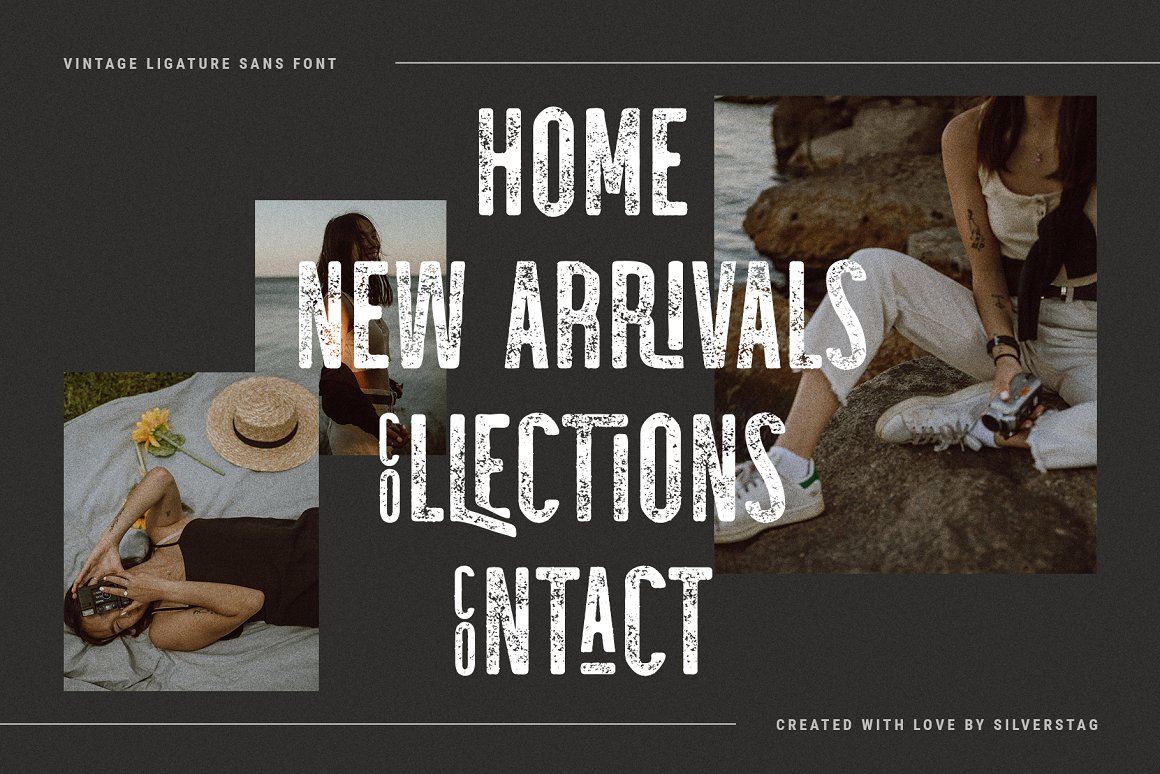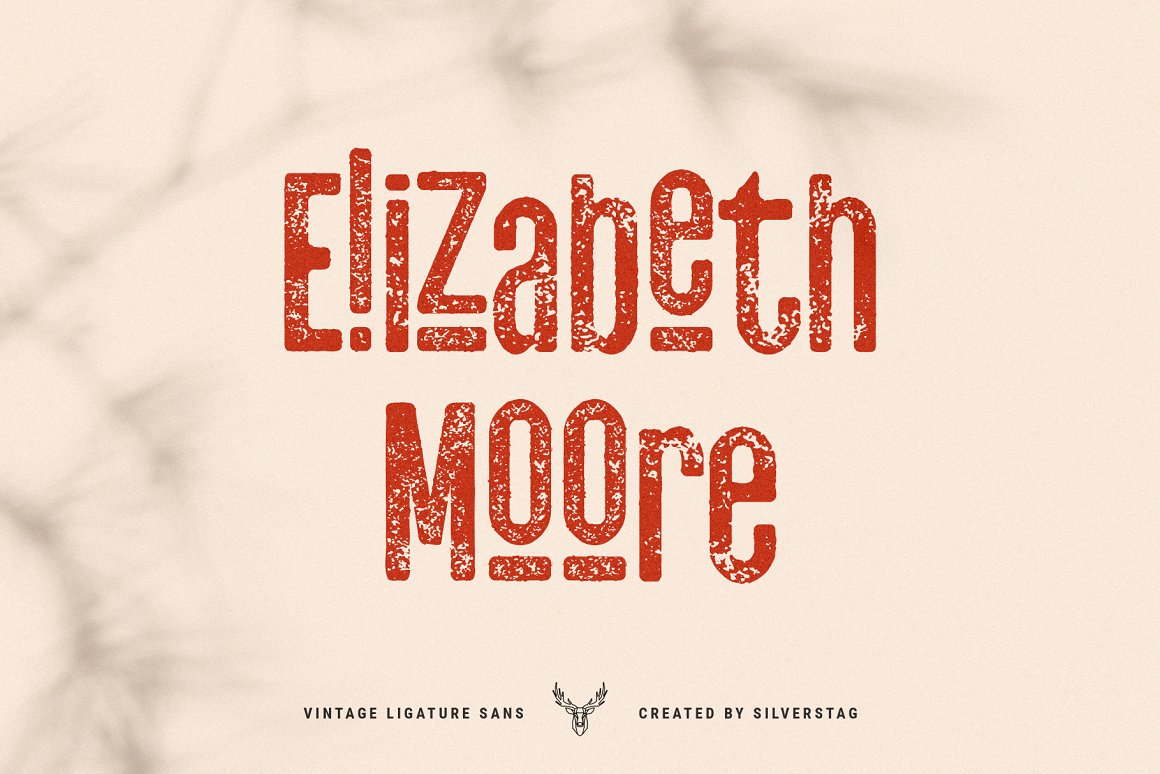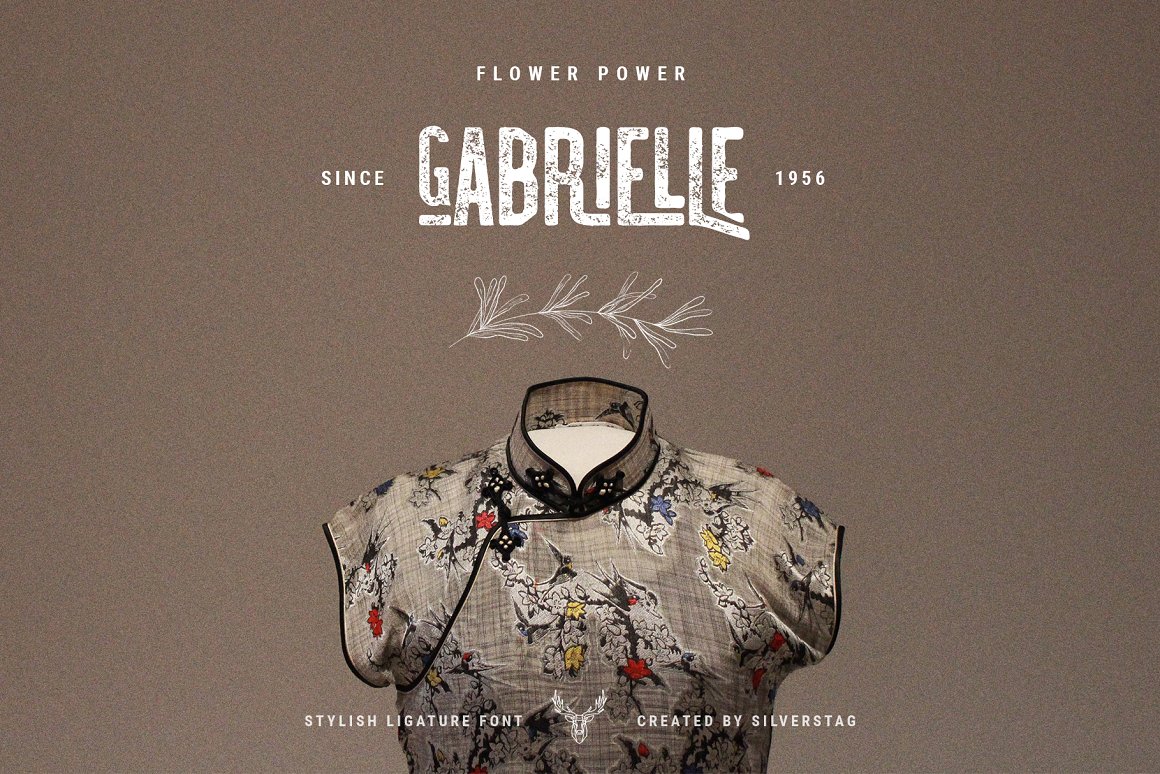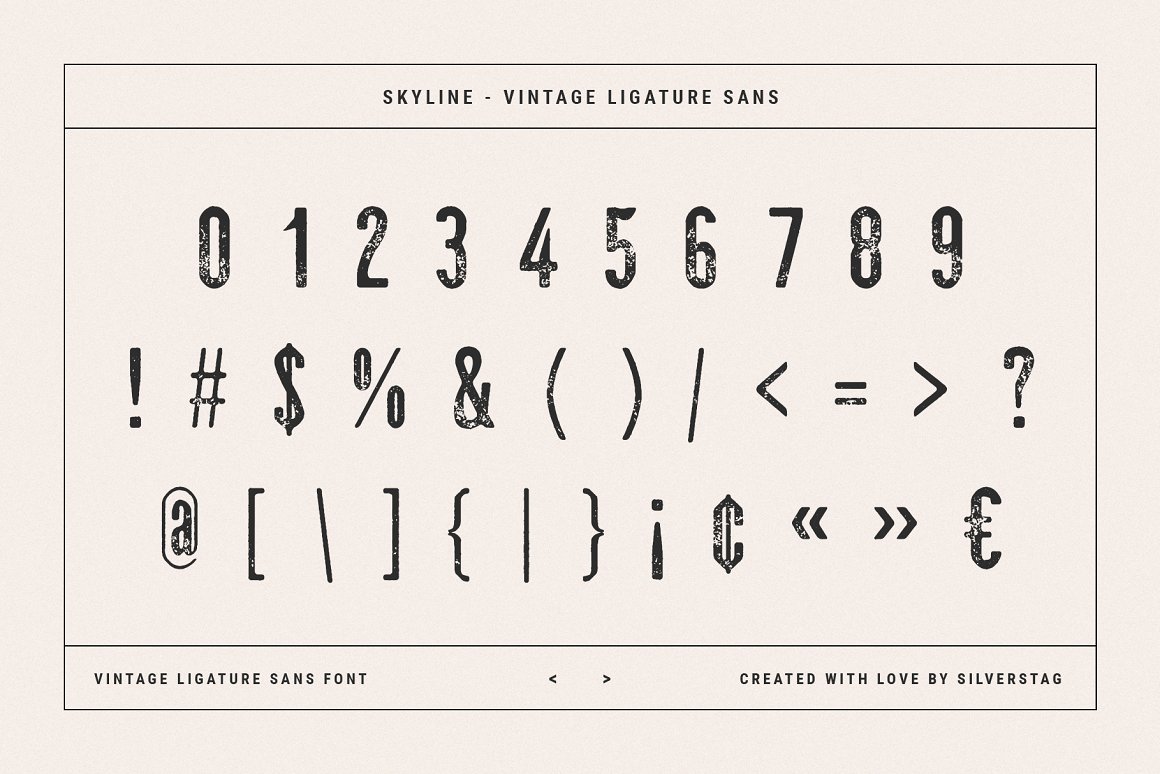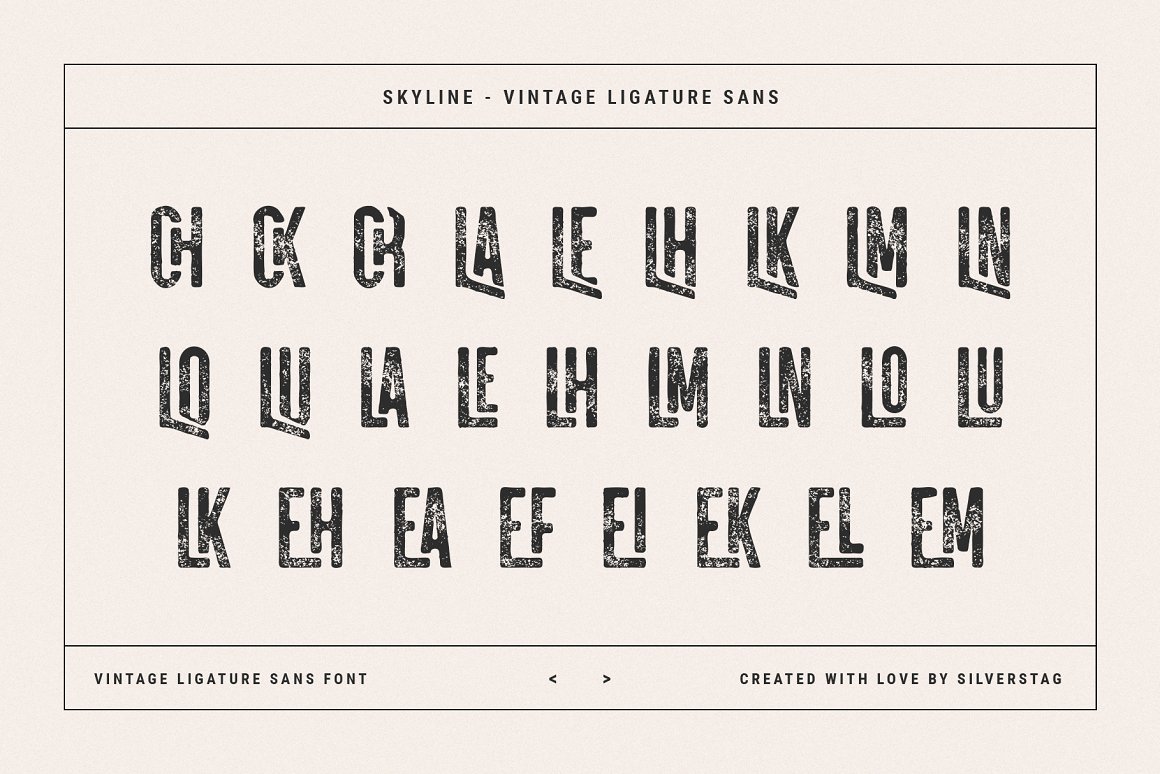
老式连字sans字体 skyline vintage ligature sans font
天际线是一种全新的,精巧的老式连字字体,包括100多个连字和备用字母,每个字母都有其独特的纹理和形状。
凭借其独特而富有创意的连字,天际线脱颖而出,也将使您的项目脱颖而出。只需看一下产品图片上的连字,您就会发现它具有什么样的潜力。